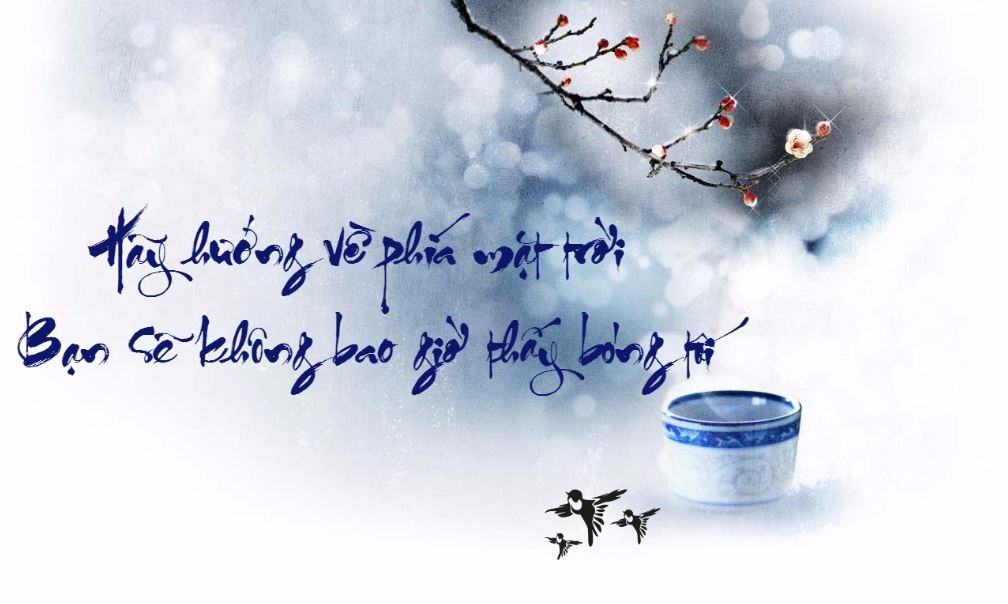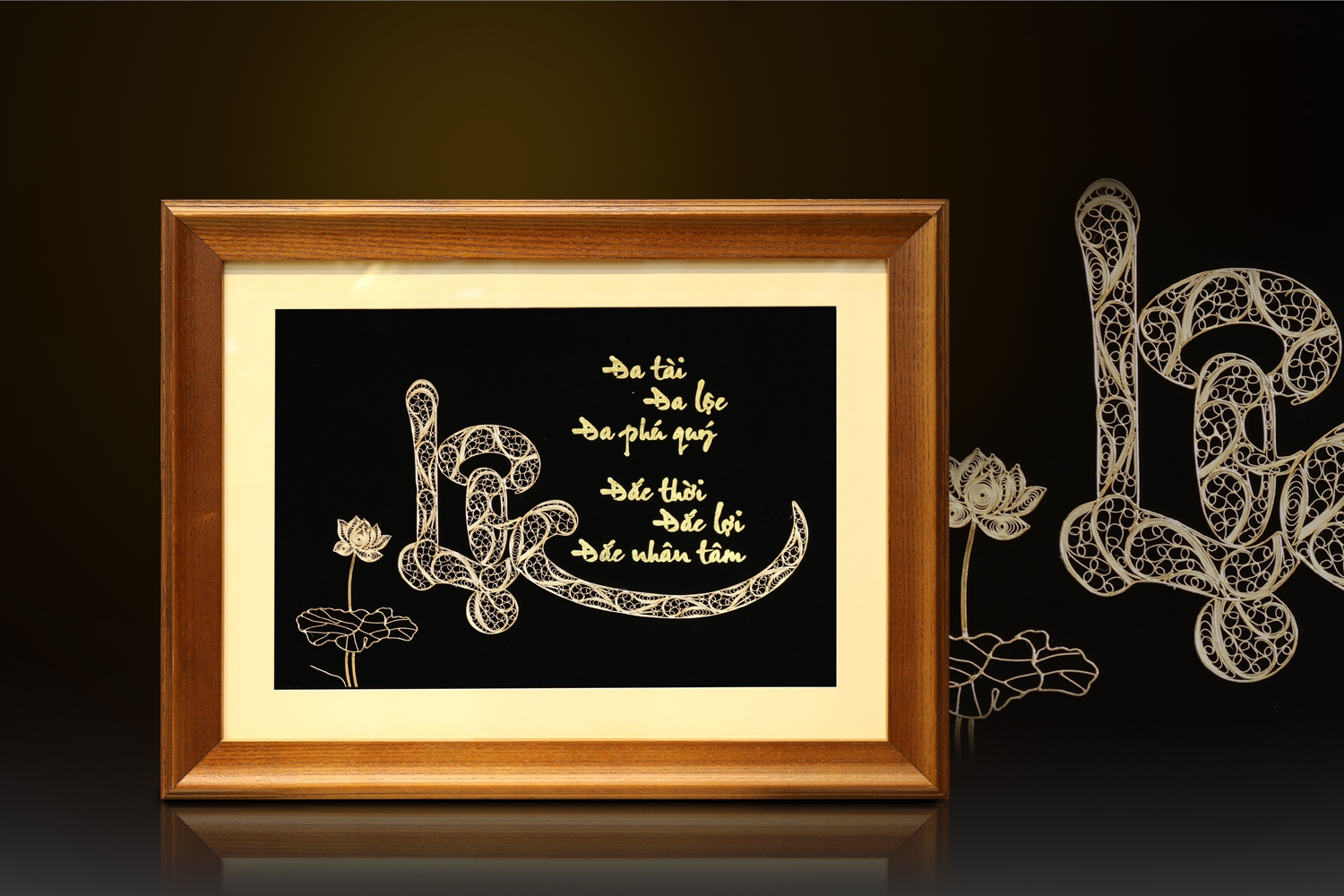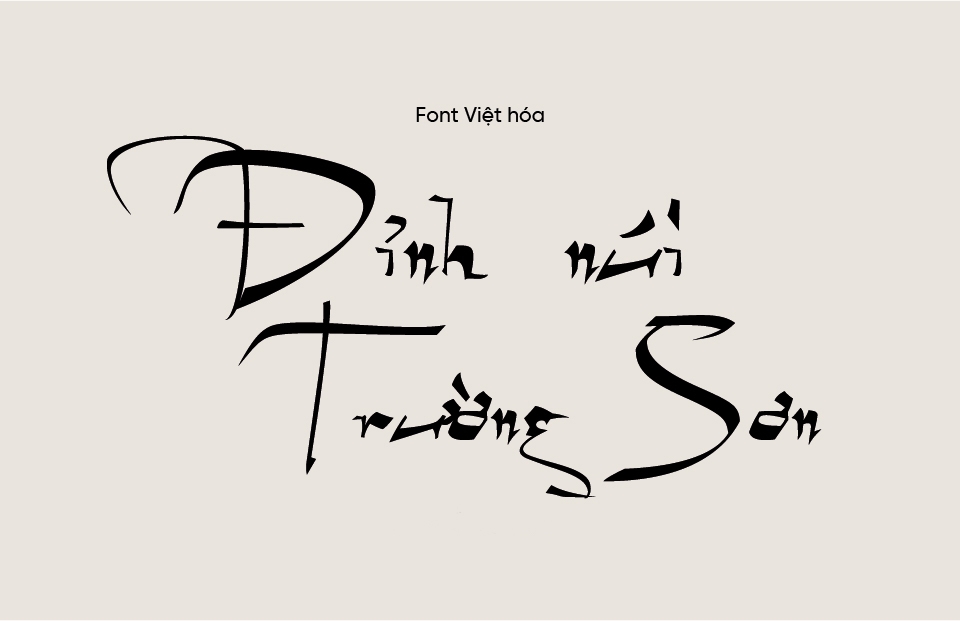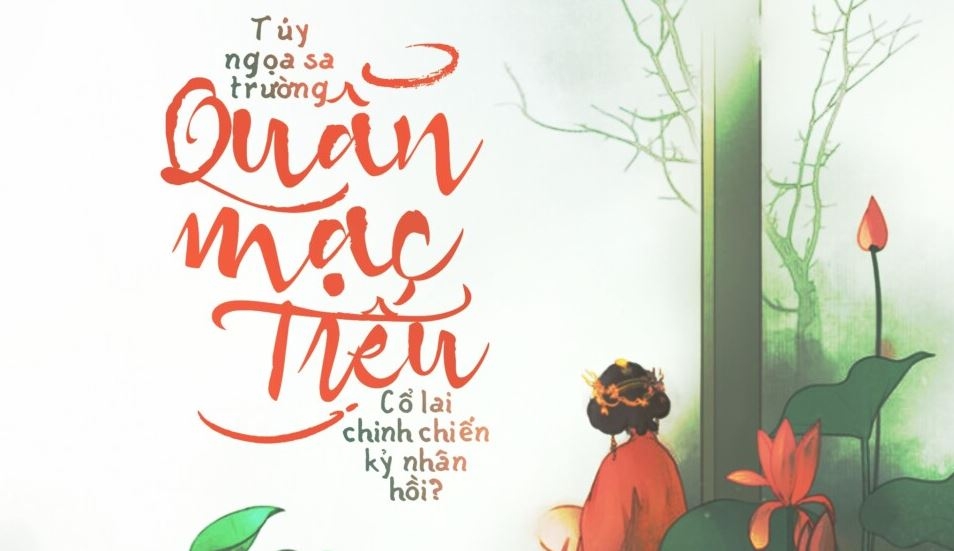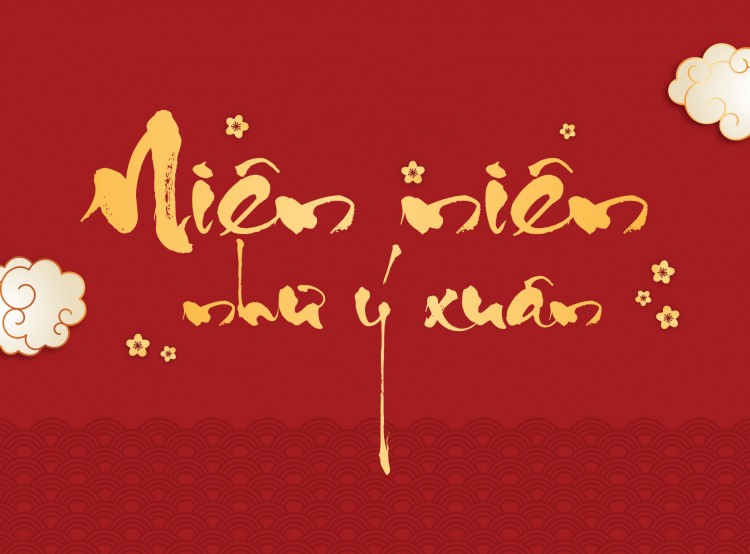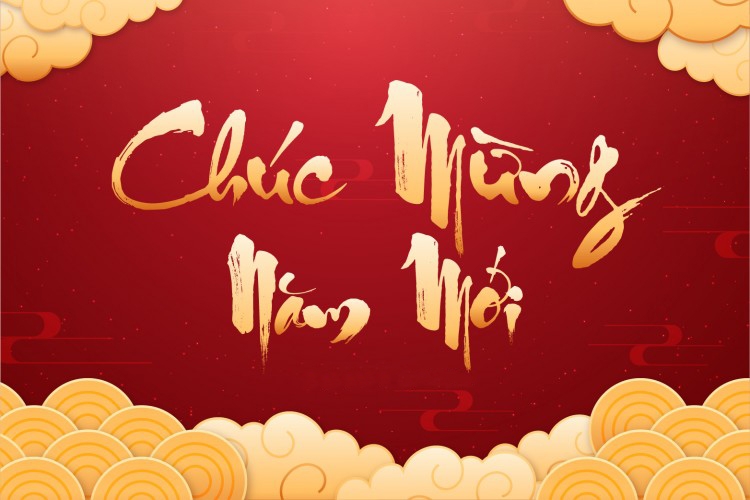
Font chữ thư pháp là gì? Lợi ích và ứng dụng của font chữ thư pháp trong đời sống
Font chữ thư pháp là loại phông chữ được lấy cảm hứng từ nghệ thuật thư pháp truyền thống với những đường nét uyển chuyển, mềm mại mang đậm dấu ấn thời gian. Theo thời gian, font chữ thư pháp được ứng dụng sáng tạo trong thiết kế hiện đại, tạo nên sức hút độc đáo cho các ấn phẩm.
Nghệ thuật thư pháp đã xuất hiện từ hàng ngàn năm trước và đặt nền móng để font chữ thư pháp phát triển. Từ những nét chữ được viết tay bởi các nghệ nhân thư pháp, font chữ thư pháp đã được thiết kế trên máy tính, điện thoại để đáp ứng được nhu cầu người dùng trong thời đại công nghệ.
Giới thiệu về font chữ thư pháp
font chữ thư pháp 01
Font chữ thư pháp nổi bật bởi các đường nét uốn lượn tinh tế, tạo nên vẻ đẹp riêng biệt và lôi cuốn. Đặc trưng nhất của font chữ là sự tự do trong cách sắp xếp bố cục và ký tự. Điều này thể hiện sự phóng khoáng và linh hoạt của người sáng tạo. Bên cạnh đó, font chữ thư pháp thường được thiết kế theo phong cách cổ điển để tạo cảm giác hoài cổ, sang trọng và đề cao giá trị nghệ thuật riêng biệt.
Ngày nay, với công nghệ phát triển, font chữ thư pháp đã được sáng tạo ra hàng trăm bộ font khác nhau, đáp ứng được nhu cầu của người sử dụng. Vì vậy, bạn đừng lo lắng sử dụng font chữ thư pháp gây nhàm chán. Bạn có thể sử dụng font chữ bằng cách download font trên các website, hay tạo trên các phần mềm Adobe Illustrator, Adobe Photoshop,...
Có thể nói, font chữ thư pháp không chỉ đơn giản là các ký tự viết mà còn là biểu tưởng của nghệ thuật, sang trọng và tinh tế.
Lợi ích khi sử dụng font chữ thư pháp
font chữ thư pháp 02
Trong từng lĩnh vực, ngành nghề, font chữ thư pháp mang đến nhiều lợi ích cho người dùng. Cụ thể:
Tăng giá trị thẩm mỹ
Font chữ thư pháp có những đặc điểm rất riêng biệt, từ các đường nét mềm mại, rồng bay phượng múa, đến các nét thanh nét đậm được nhấn nhá có chủ đích riêng. Điều này vô cùng hữu ích khi người thiết kế muốn thu hút sự chú ý của người xem và làm tăng giá trị thẩm mỹ, nổi bật các ấn phẩm.
Truyền tải thông điệp hiệu quả
So với font chữ thông thường, font chữ thư pháp có tính truyền tải thông điệp cao, hiệu quả hơn. Các nét chữ có sự uyển chuyển, mềm mại, cách điệu trong từng chi tiết thể hiện được cảm xúc, ý đồ riêng của người thiết kế.
Tạo sự độc đáo, khác biệt
Mỗi font chữ thư pháp có những nét đẹp riêng, mang đến cái nhìn độc đáo, từ đó thể hiện được phong cách và gu thẩm mỹ của người sáng tạo. Mỗi tác phẩm được thiết kế ra giúp tăng tính cá nhân hóa, tạo dấu ấn riêng.
Khơi gợi cảm xúc, vẻ hoài cổ
Font chữ thư pháp thường có các nét uốn lượn, mềm mại như bút lông vẽ tạo nên sự hoài cổ, sang trọng. Ngoài ra, chữ thư pháp ban đầu cũng đã gợi nên cảm giác lãng mạn, dịu dàng nhưng cũng thể hiện sự uy nghiêm thông qua các ngữ cảnh, mục đích sử dụng khác nhau.
Ứng dụng của font chữ thư pháp trong đời sống
font chữ thư pháp 03
Trong thời đại công nghệ phát triển, font chữ thư pháp không chỉ giới hạn trong việc ghi chép thông thường mà còn ứng dụng đa dạng vào các ngành nghề, lĩnh vực trong cuộc sống. Font chữ được ứng dụng nhiều trong:
Thiết kế thiệp mời, ấn phẩm marketing
Ứng dụng phổ biến nhất của font chữ thư pháp trong đời sống hiện đại là thiết kế đồ họa. Font chữ thường mang đến cảm giác sang trọng, cổ điển cho các dự án thiết kế như poster, banner, website, thiệp mời,... Việc sử dụng các font chữ thư pháp trong thiết kế không chỉ làm cho ấn phẩm thu hút mà còn mang lại sự tinh tế cho người nhìn.
Vẽ tranh thư pháp
Ngoài sử dụng trong các thiết kế đồ họa, font chữ thư pháp cũng được ứng dụng để tạo nên các tác phẩm nghệ thuật, tranh vẽ cuốn hút. Các đường nét rồng bay phượng múa của chữ thư pháp tạo ra những bức tranh chữ độc đáo hay tác phẩm nghệ thuật trừu tượng mang lại sự mới mẻ và phong cách riêng biệt.
Trang trí nội thất, không gian sống
Font chữ thư pháp được sử dụng để tạo ra các sản phẩm trang trí nội thất, không gian sống đẹp, sang trọng. Bạn có thể mua các chữ, câu danh ngôn, câu đối, đoạn văn được thể hiện qua font chữ để treo, trang trí trên tường. Đây sẽ là điểm nhấn ấn tượng cho không gian sống của bạn.
Các font chữ thư pháp đẹp, phổ biến
Có rất nhiều font chữ thư pháp để bạn sử dụng trong các ấn phẩm. Dưới đây là 5 font chữ thư pháp đẹp, được nhiều người lựa chọn. Cụ thể:
Font chữ MTD Geza Script
font chữ thư pháp 04